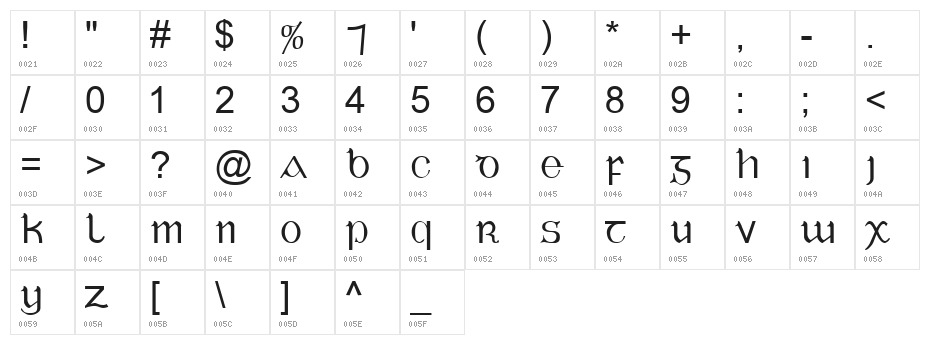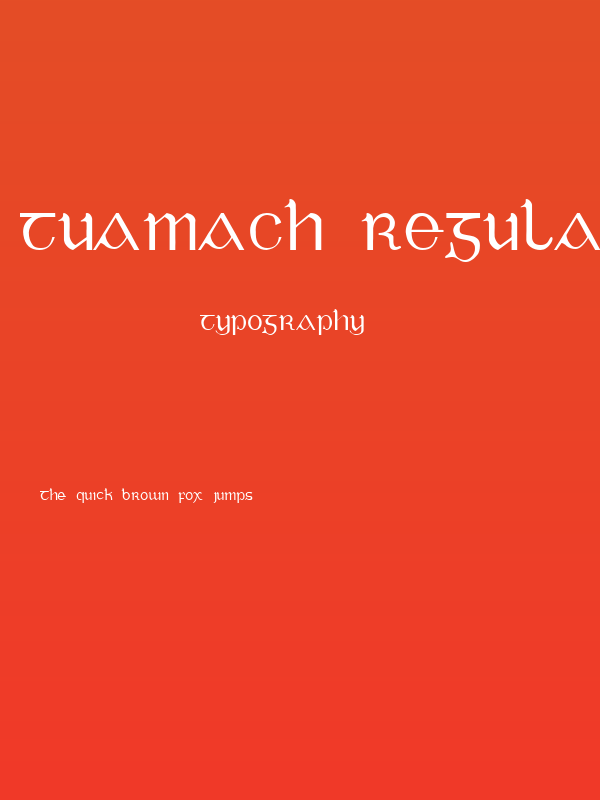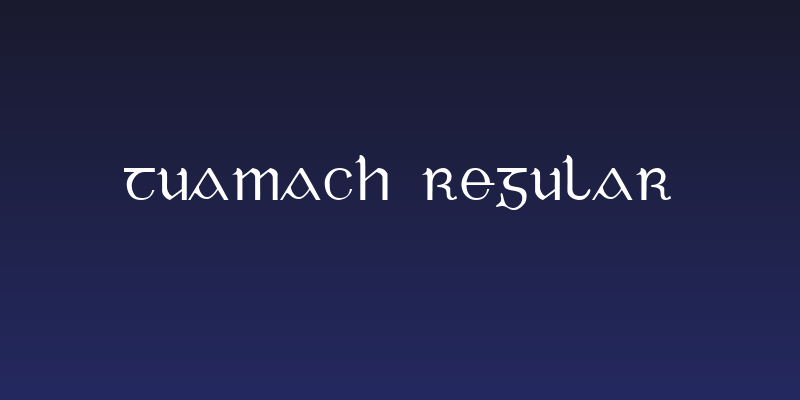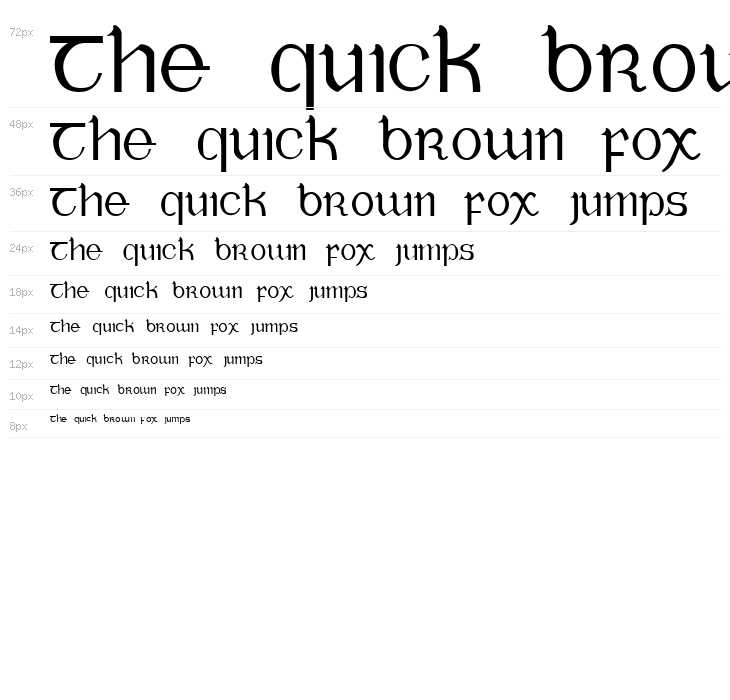
Tuamach Regular Font
✎ Serif
| 分类 | Serif |
| 使用场景 | Headlines, Logos, Editorial design |
| 推荐项目 | Ideal for branding, editorial design, and high-end product packaging. Its distinctive style makes it suitable for logos and headlines that require a touch of elegance and modernity. |